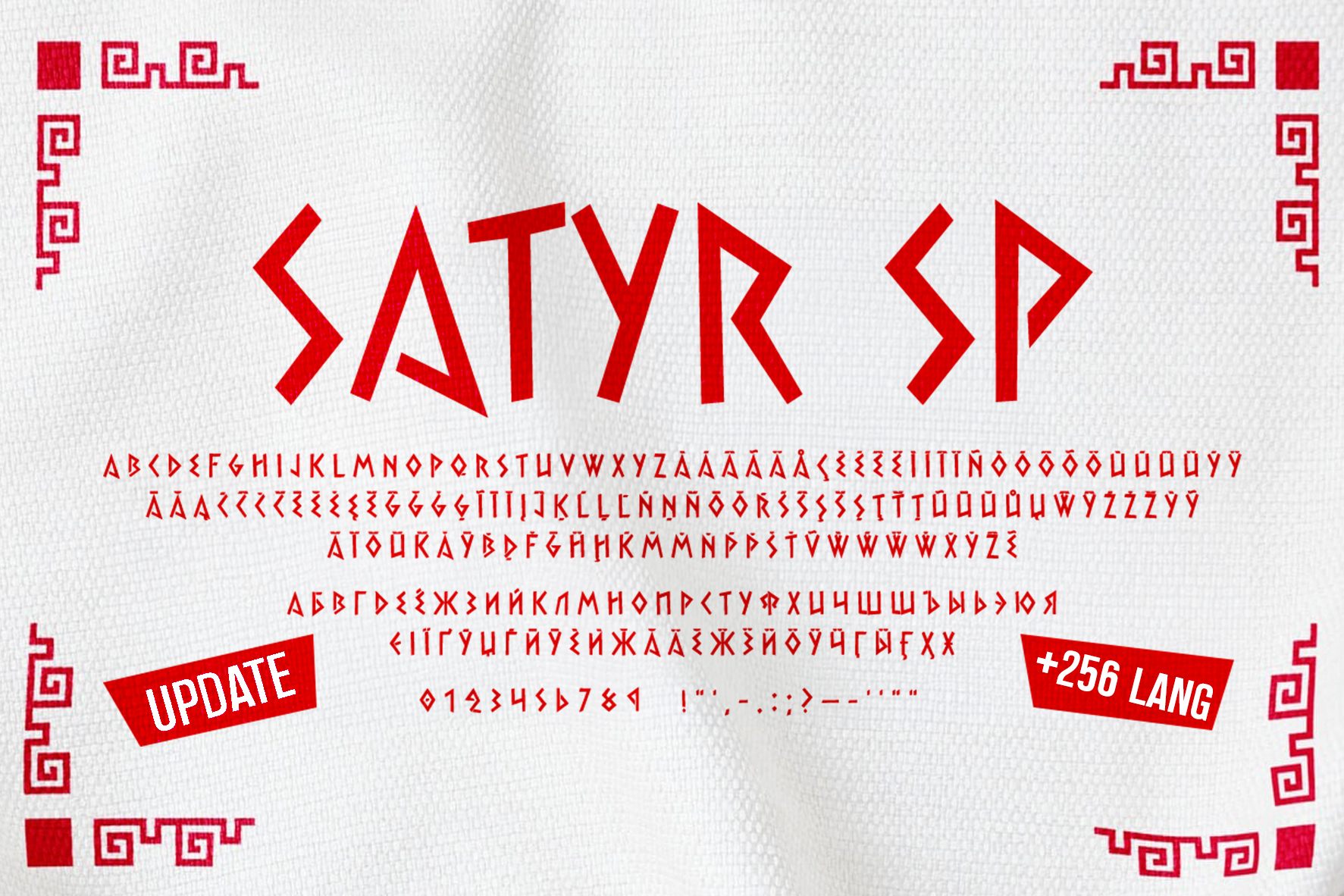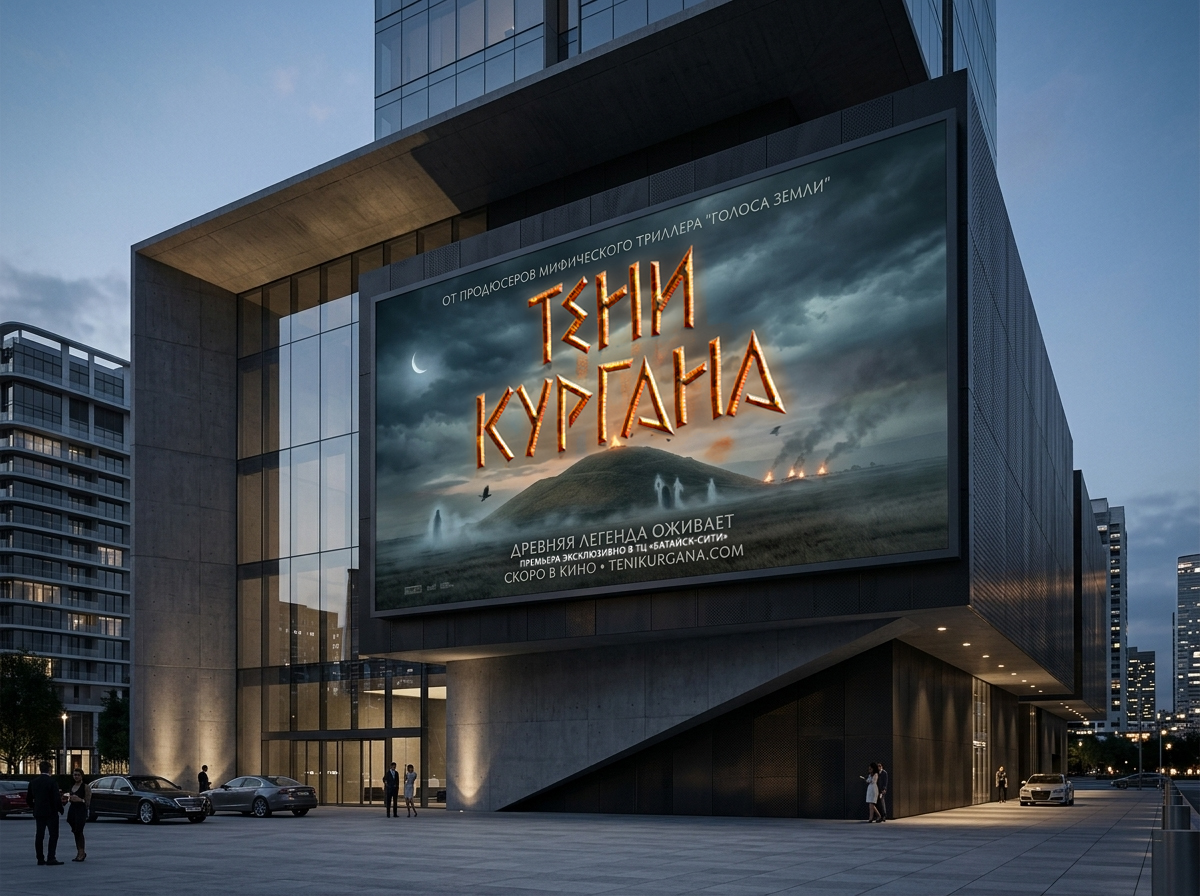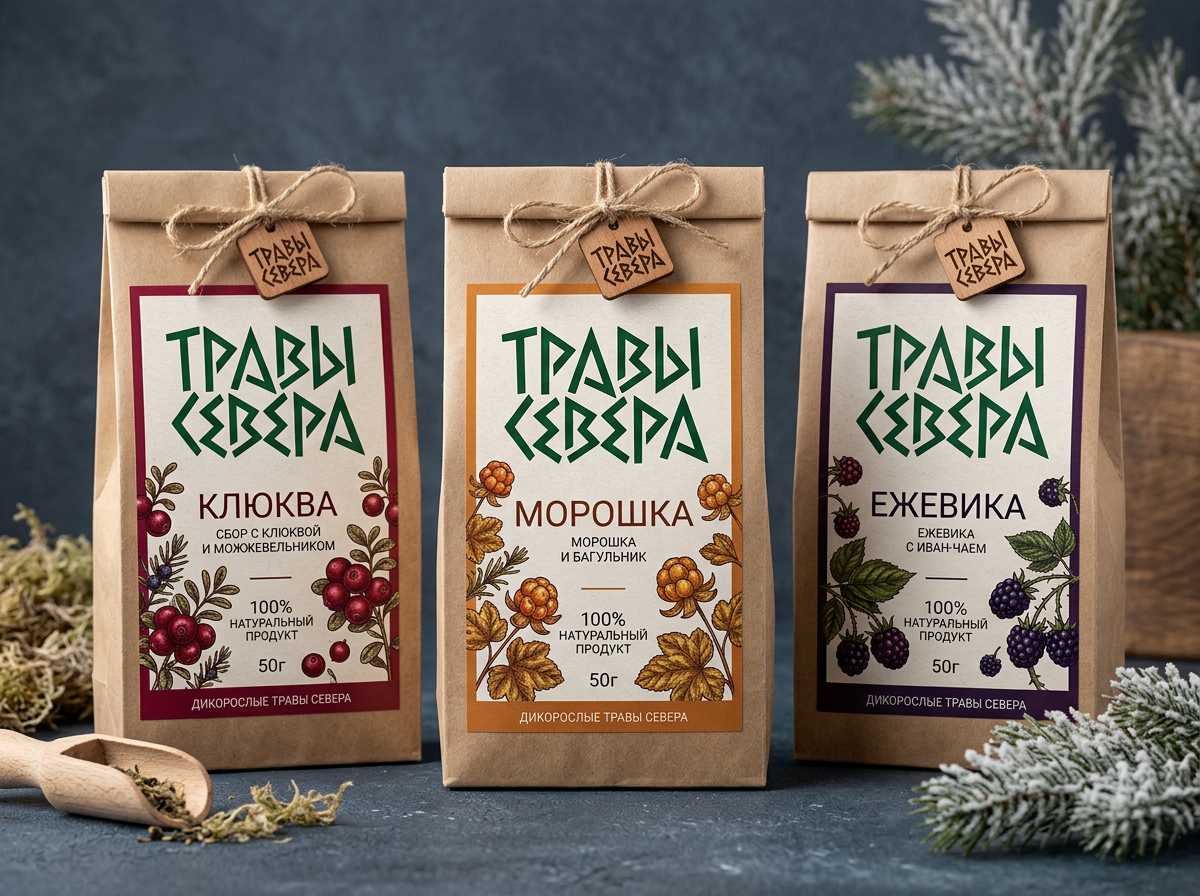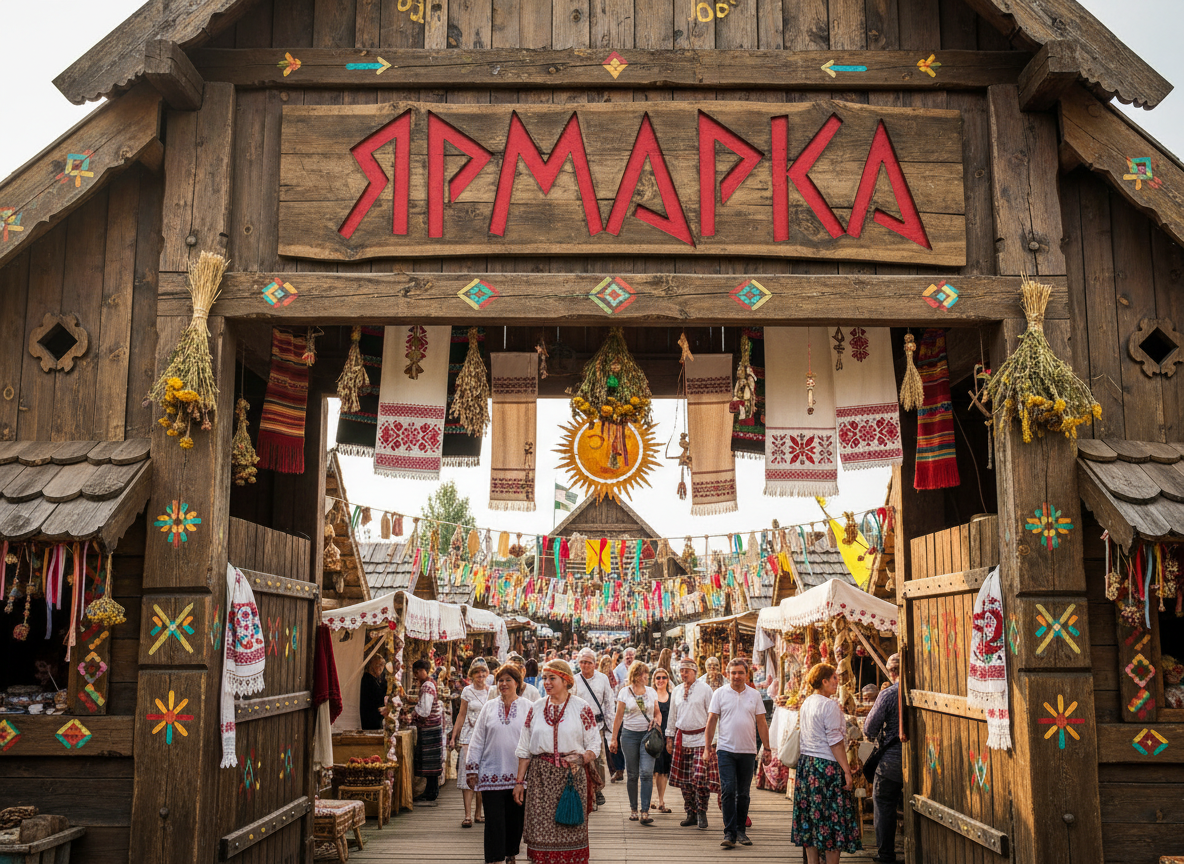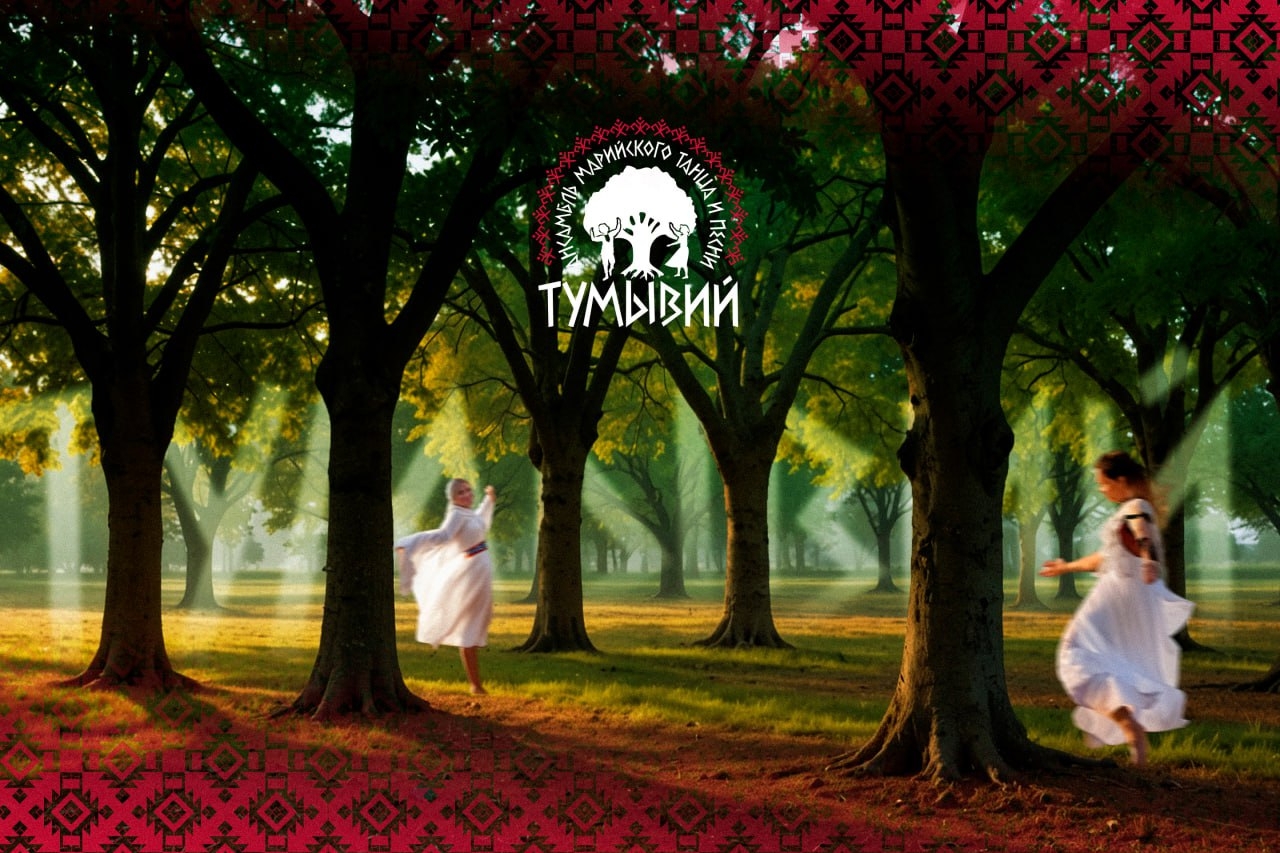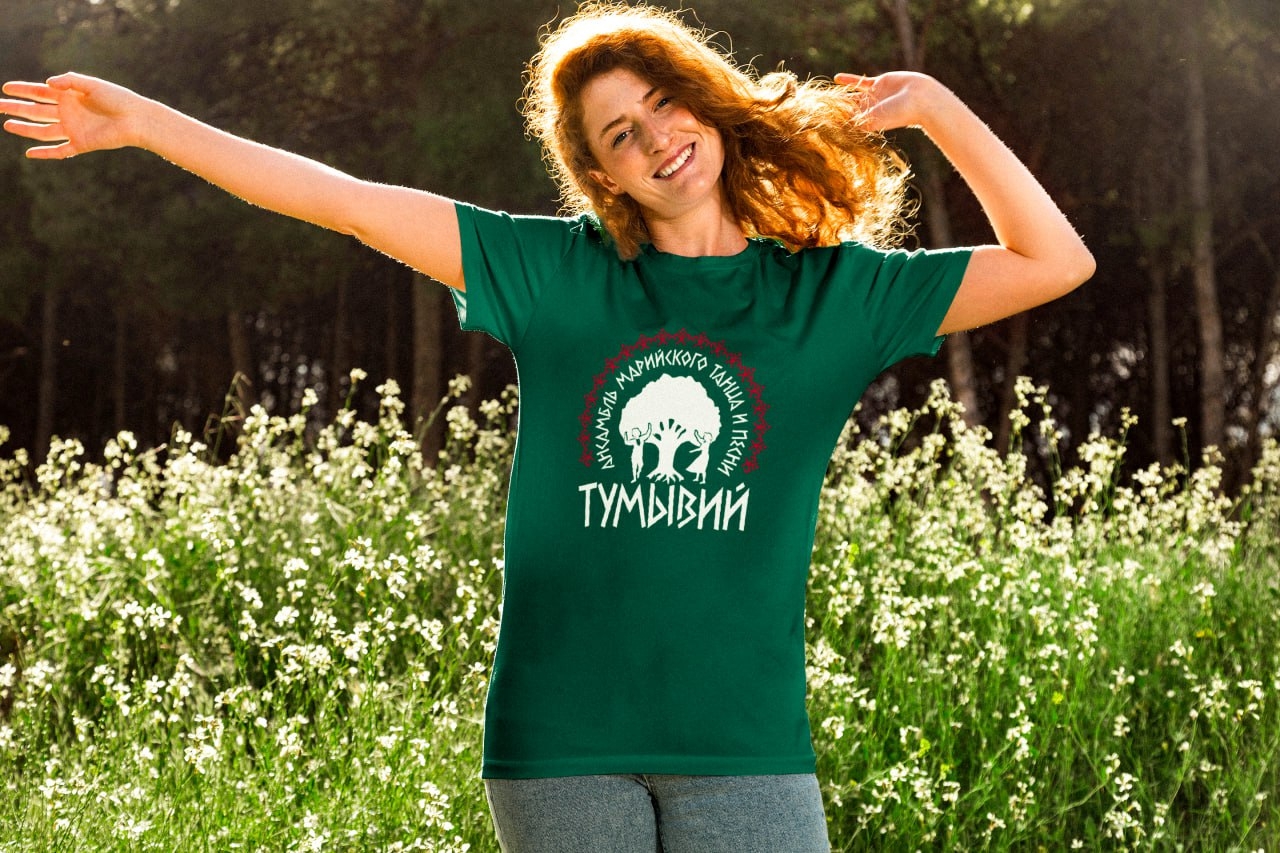
Satyr SP — акцидентный шрифт с острыми, ломаными формами и живым неровным ритмом. В его рисунке чувствуется связь с народными мотивами, орнаментом и образами древних культур Европы, поэтому строка выглядит смело, немного сурово и очень выразительно. Шрифт особенно уместен в логотипах, упаковке, брендинге и проектах с этническим, сказочным или фольклорным характером. В комплекте — расширенная версия шрифта и электронная лицензия. Подойдет дизайнерам айдентики, упаковки и визуальных систем, которым нужен рукотворный и небуквально исторический акцент.